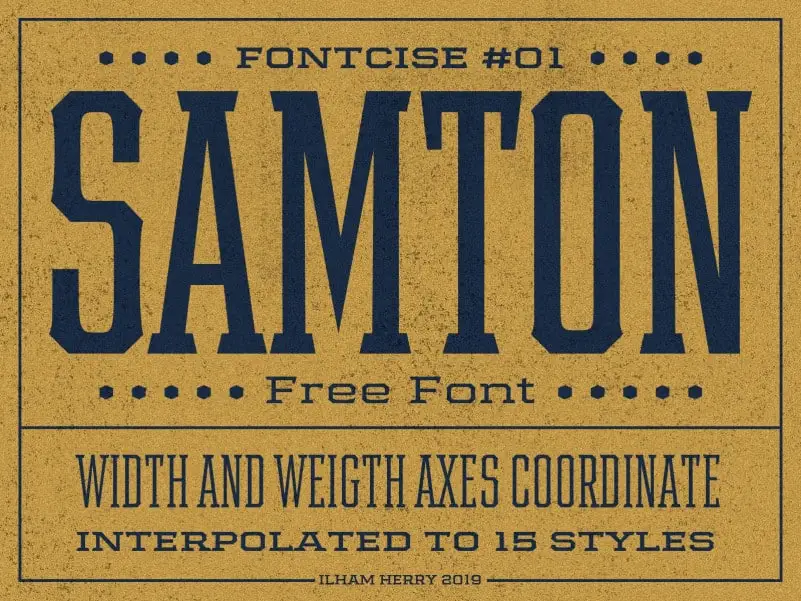
Samton Display Font Family – Download Grátis
Samton Display Font é uma fonte de exibição simples e casual que transmite uma sensação militar. Desenhada pelo Ilham Herry, esta experimentada família de fontes foi criada durante um exercício sobre coordenadas cartesianas. Samton apresenta eixos de peso e espessura com quatro mestres interpostos em 15 diferentes tipos de letra. Este tipo de escrita perfeitamente se adequa ao design em estilo vintage, artesanato, cartazes retro, headlines e outros projetos autênticos. Com um toque casual porém profundo, Samton Display Font se destaca como uma escolha ideal para designers que buscam transmitir um certo espírito militar através de suas criações. Seja você designer gráfico ou artesão, esta fonte oferece a liberdade criativa necessária para traduzir seus projetos em um estilo vintage e retro com a certeza de que seu trabalho terá o toque perfeito.